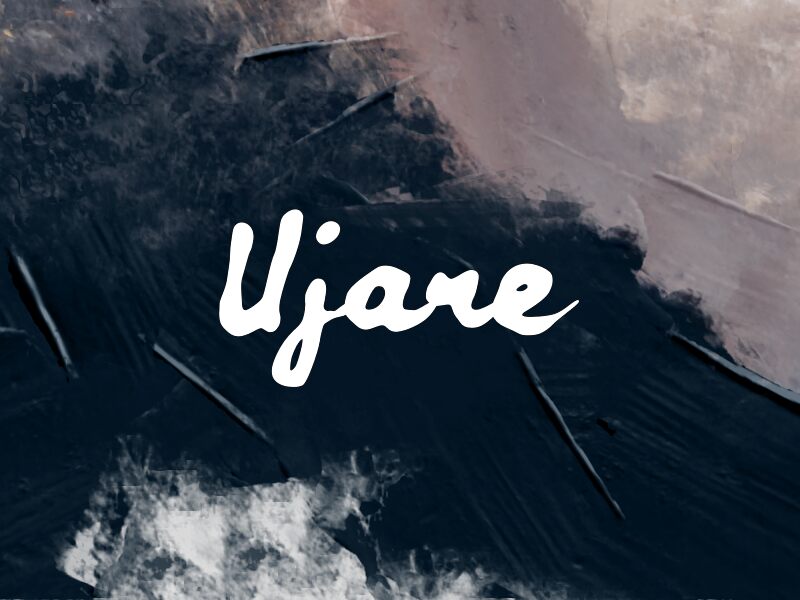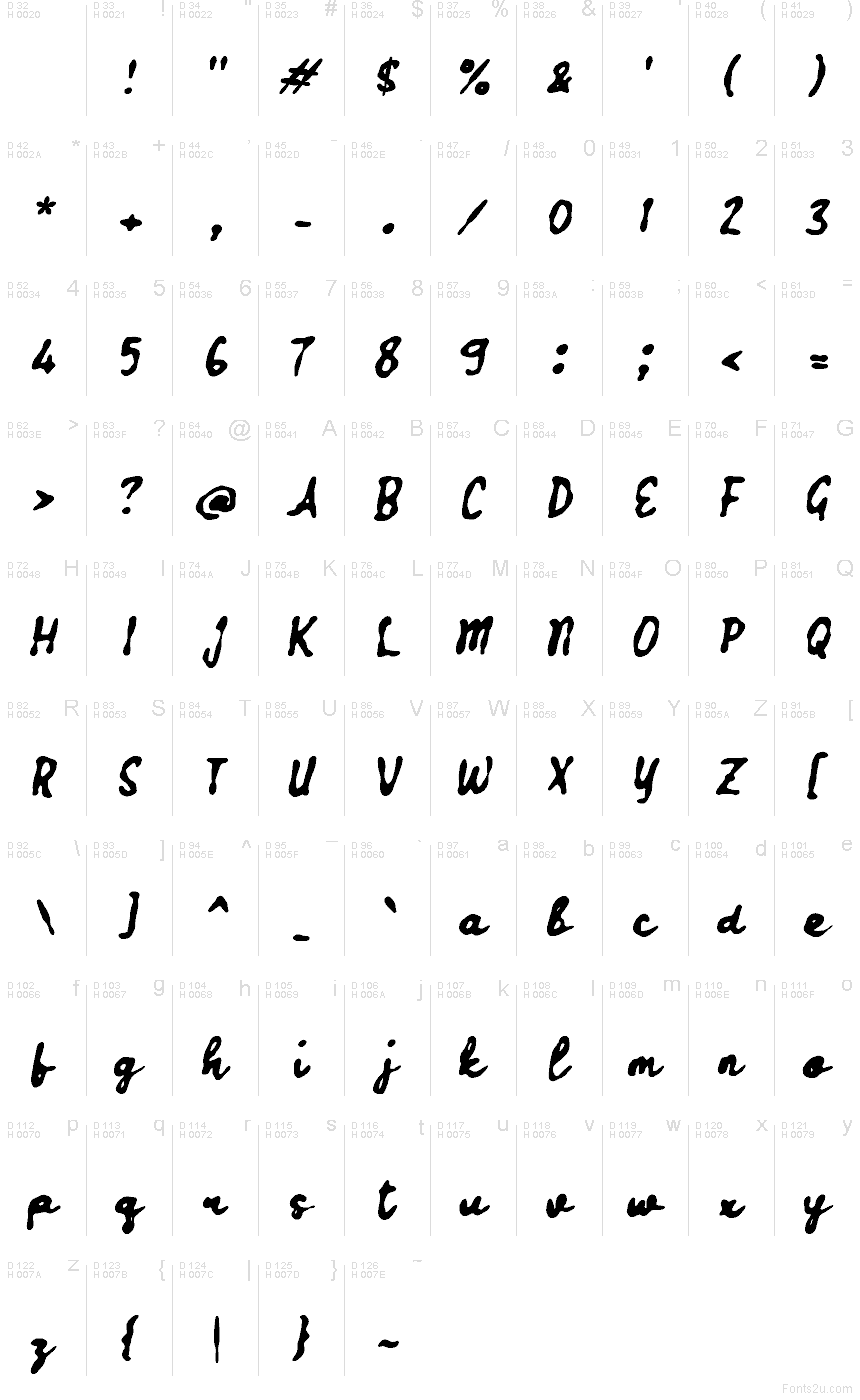
Ujare
Ujare de ikiik es una tipografía brush gratuita con un ritmo bajo y fluido que mantiene las letras juntas, sin caer en lo aireado o formal. Sus trazos anchos y giros redondeados le dan un aire suave y entintado, mientras que el movimiento de las terminaciones añade la fricción justa para mantener la escritura viva.
Este movimiento funciona de maravilla en logotipos de cafeterías, packaging, titulares de pósteres, gráficos para redes sociales e invitaciones informales, donde se busca una sensación artesanal en lugar de algo excesivamente pulido. Las líneas de marca cortas se benefician especialmente de su flujo compacto, ya que sus formas conectadas crean una firma rápida y con mucha seguridad.